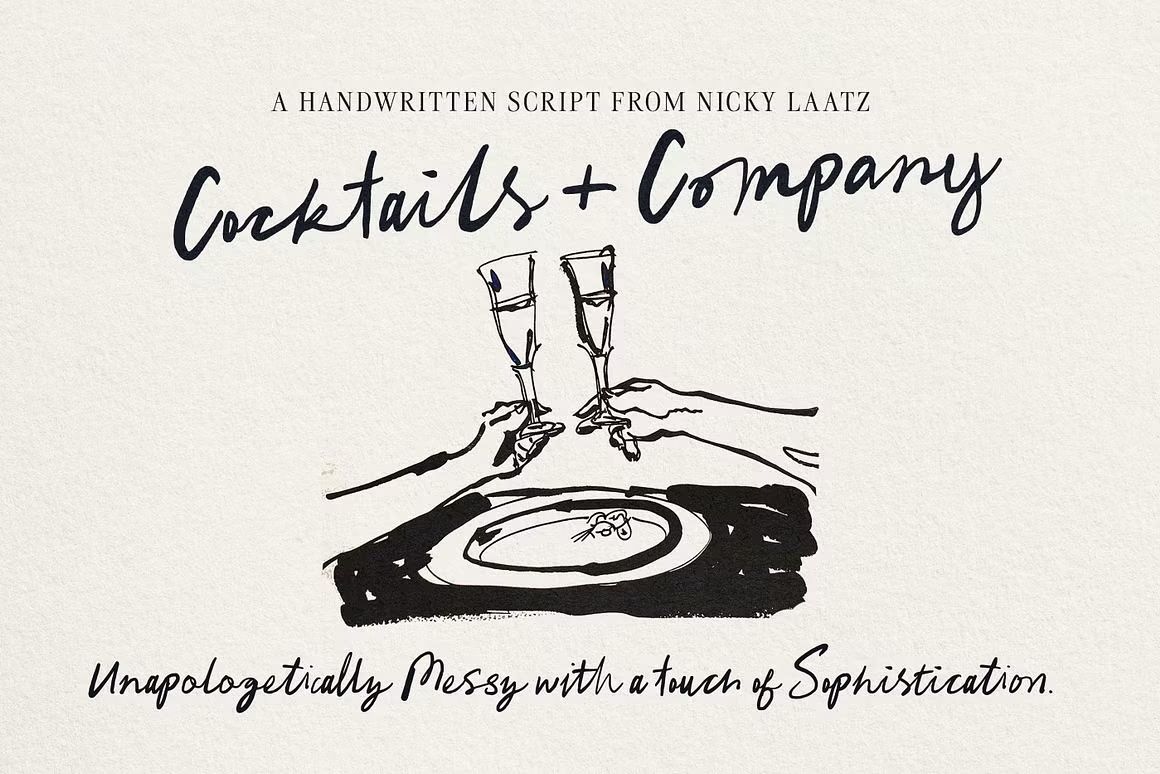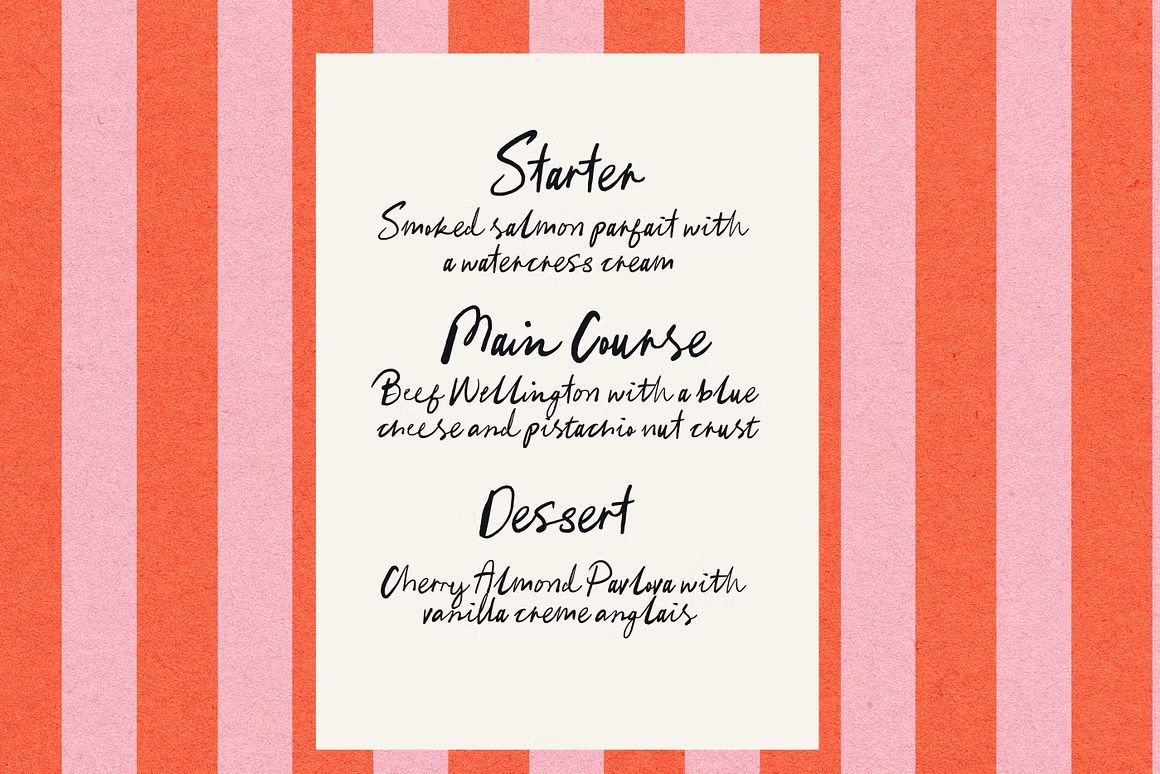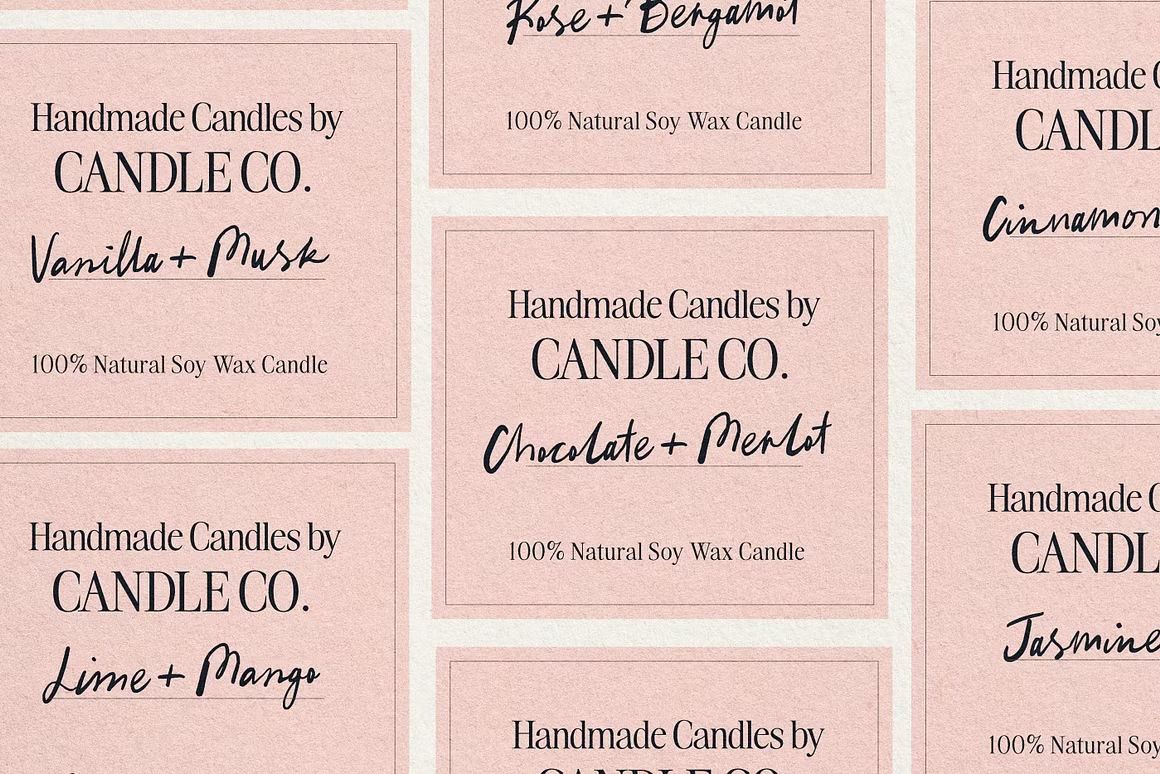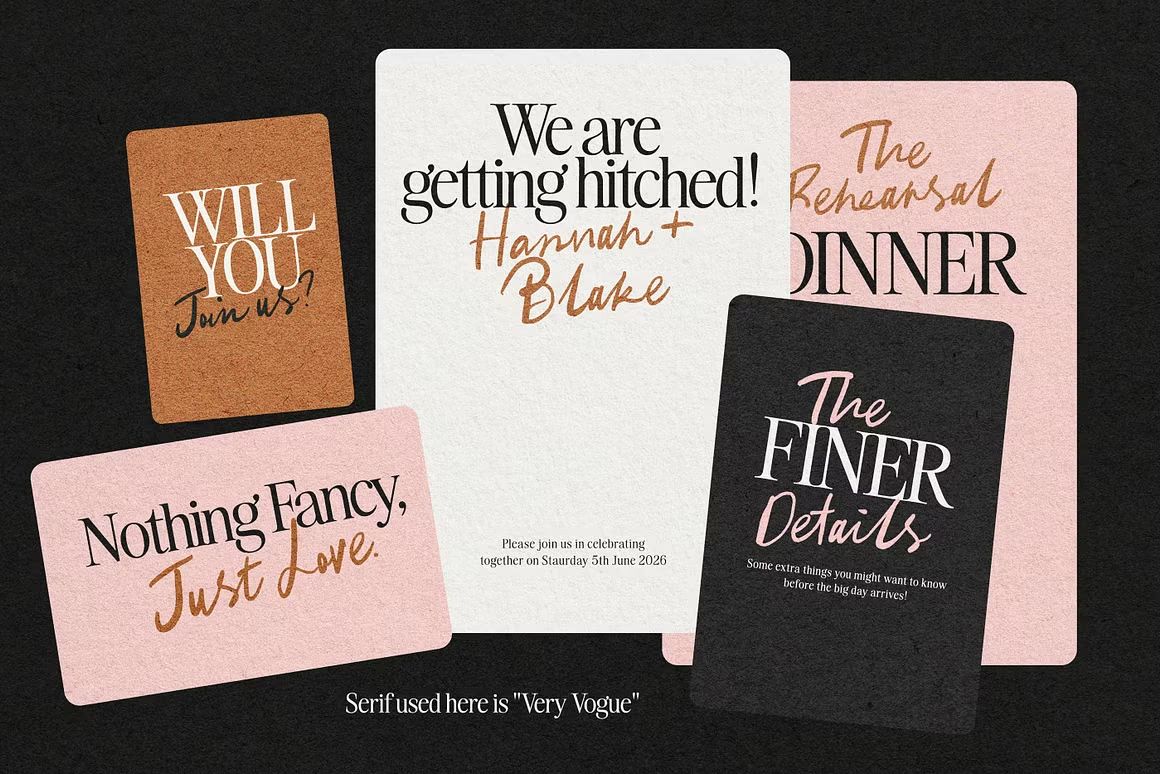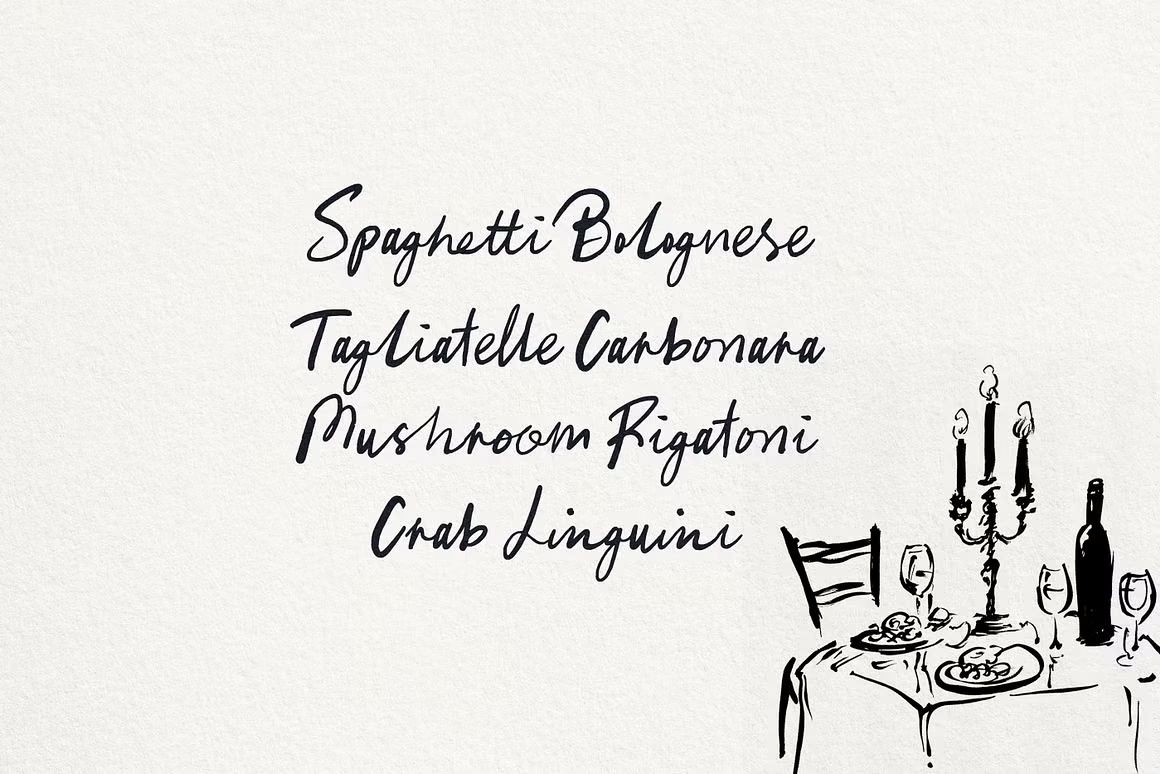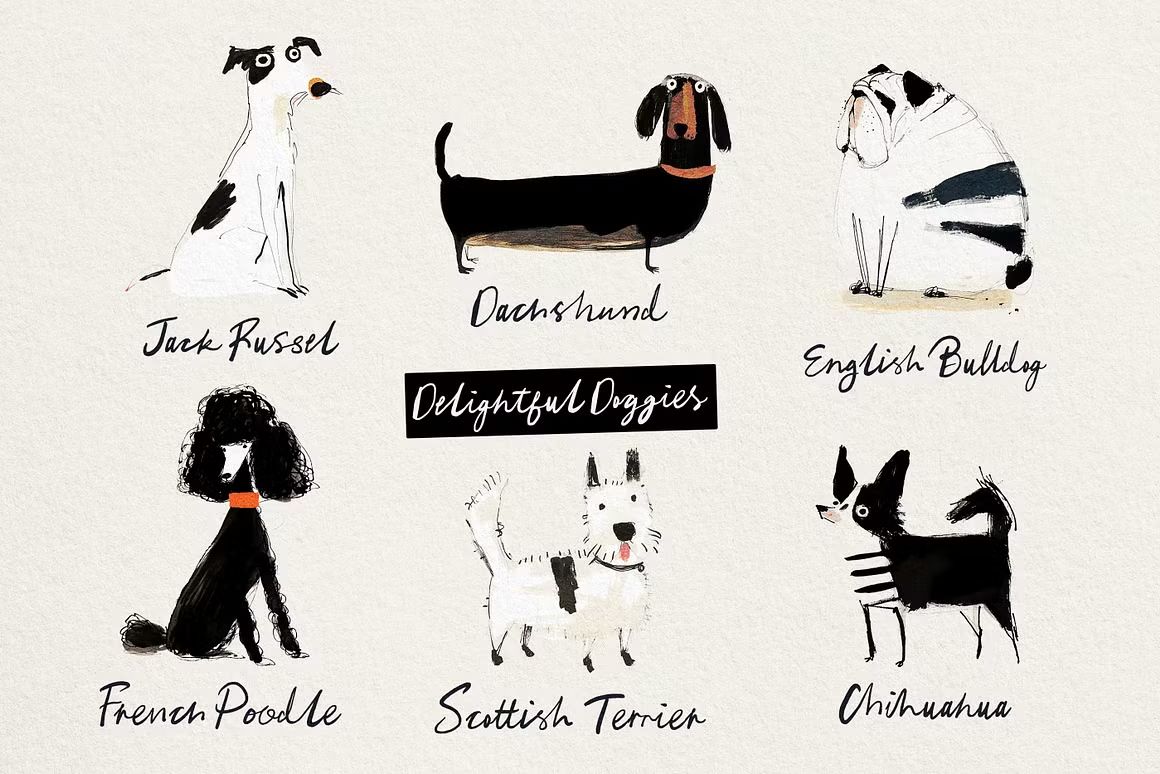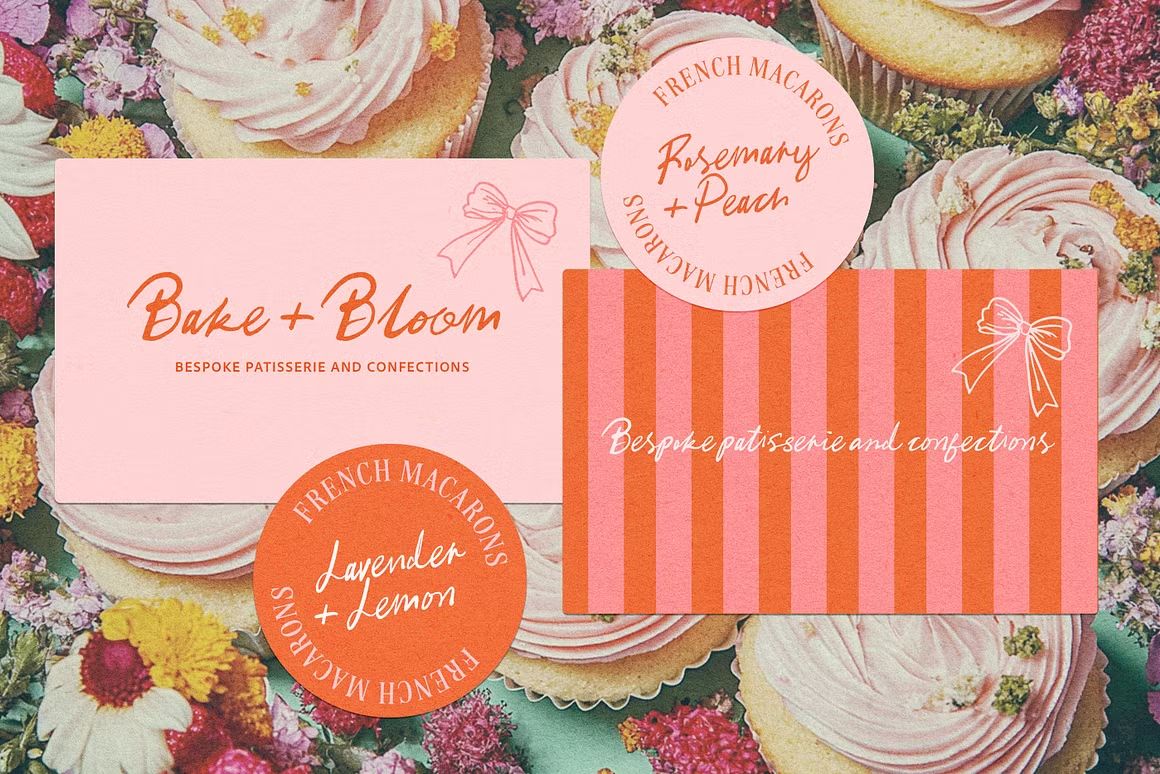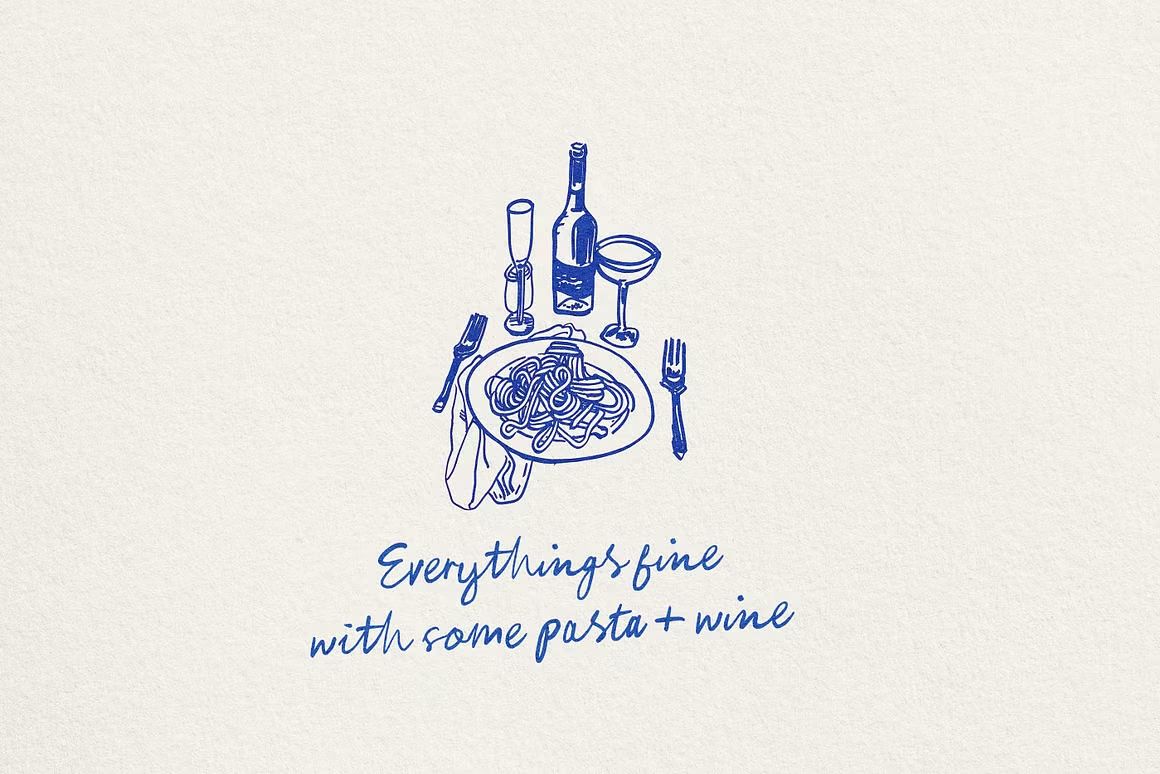
Cocktails and Company – Script Font
Cocktails and Company adalah font script bergaya santai dan elegan, dengan sapuan tulisan tangan yang halus dan mengalir. Didesain untuk memberikan kesan ramah namun tetap stylish, font ini cocok untuk undangan, menu restoran, branding minuman, kutipan estetik, dan desain media sosial. Tampilannya yang playful namun profesional menjadikannya ideal untuk berbagai proyek kreatif.
• Script font dengan gaya santai dan elegan
• Cocok untuk branding kuliner, undangan, dan media sosial
• Termasuk huruf besar, kecil, angka, simbol, dan ligatur